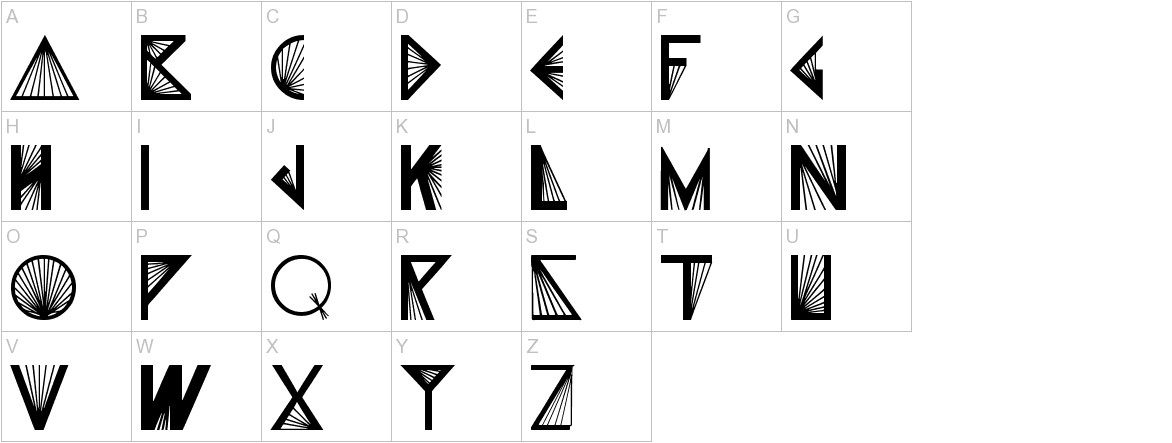
X-PRISM
Inspirado no logotipo da turnê da cantora Katy Perry (Prismatic). As restantes letras que não compõem o título da tour foram criadas e editadas por mim. // Inspired on the "PRISMATIC Tour" (from Katy Perry) logo. The other words are created by myself.